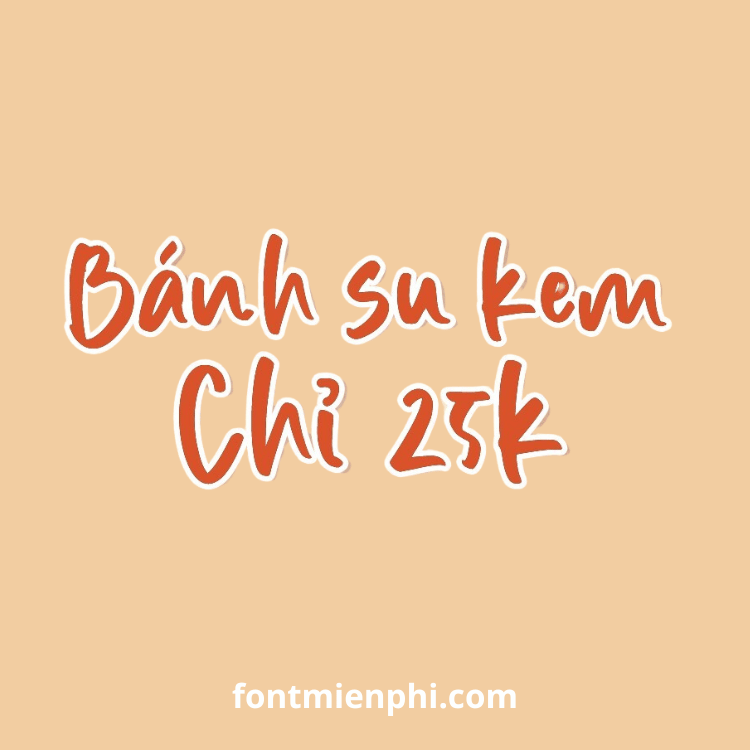
Font Việt hóa 1FTV VIP Bintang Hati
Font Việt Hóa 1FTV VIP Bintang Hati – Nét Chữ Độc Đáo, Sang Trọng
Font Việt hóa 1FTV VIP Bintang Hati là một trong những font chữ nghệ thuật được ưa chuộng nhất hiện nay, với thiết kế độc đáo, mềm mại và đầy tính sáng tạo. Font chữ này phù hợp cho nhiều mục đích sử dụng như thiết kế đồ họa, in ấn, quảng cáo, hoặc tạo điểm nhấn cho các dự án nghệ thuật.
Đặc điểm nổi bật:
• Việt hóa hoàn chỉnh: Hỗ trợ đầy đủ dấu tiếng Việt, đảm bảo tính thẩm mỹ và dễ đọc.
• Phong cách sang trọng: Nét chữ uốn lượn, kết hợp họa tiết trái tim tinh tế, mang lại cảm giác lãng mạn, phù hợp với thiệp mời, logo cửa hàng thời trang, mỹ phẩm.
Với 1FTV VIP Bintang Hati, bạn có thể tạo ra những tác phẩm typography ấn tượng, thu hút người xem ngay từ cái nhìn đầu tiên. Font chữ này đặc biệt phù hợp với các dự án cần sự mềm mại, nữ tính hoặc phong cách vintage.